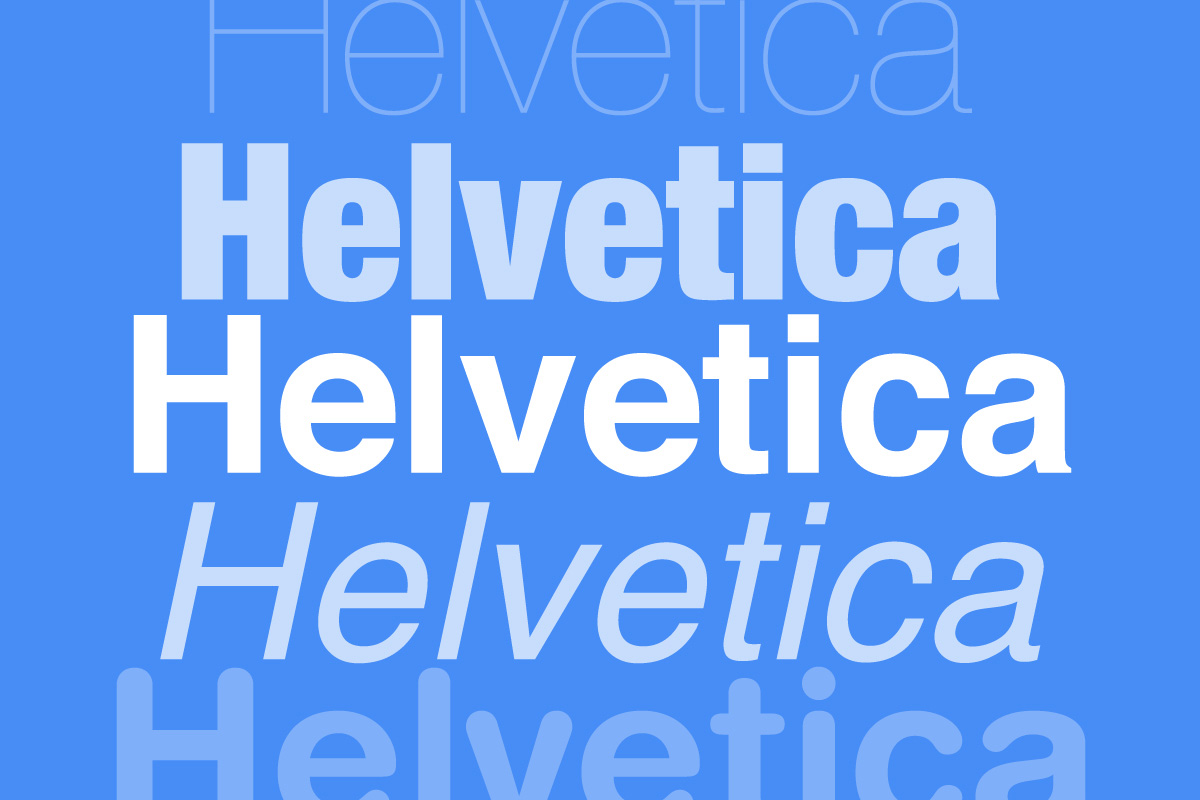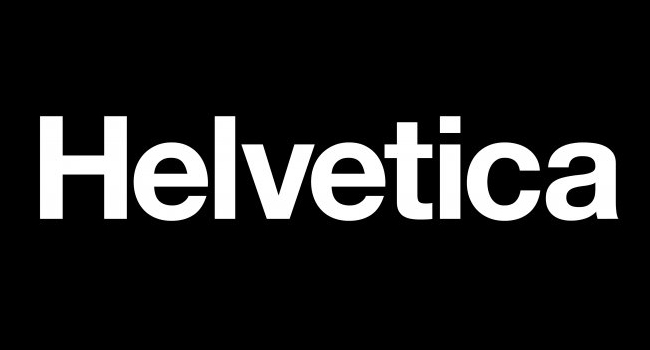
Download font Helvetica – font chữ huyền thoại được mệnh danh là “font chữ hoàn hảo nhất thế giới”, được sử dụng bởi hàng nghìn thương hiệu lớn như BMW, American Airlines, Lufthansa, Toyota. Font Helvetica với phong cách sans-serif trung tính, cân đối tuyệt đối là lựa chọn hàng đầu cho thiết kế bao bì sản phẩm cao cấp, túi giấy thương hiệu và in ấn chuyên nghiệp.
Font Helvetica là gì?
Font Helvetica được thiết kế năm 1957 bởi Max Miedinger tại Haas Type Foundry ở Thụy Sĩ. Tên gốc của font là Neue Haas Grotesk, sau đó được đổi thành Helvetica (từ “Helvetia” – tên Latin của Thụy Sĩ) vào năm 1960 khi Linotype mua bản quyền và phát hành quốc tế.
Helvetica nhanh chóng trở thành biểu tượng của thiết kế hiện đại thế kỷ 20 nhờ phong cách trung tính tuyệt đối, cân đối hoàn hảo. Font này không mang bất kỳ tính cách riêng biệt nào – không cổ điển, không hiện đại quá, không nam tính, không nữ tính – chính điều này khiến nó phù hợp với mọi thương hiệu và mọi thông điệp.
Các phiên bản Helvetica qua thời gian:
• Helvetica gốc (1957): Có các phiên bản Regular, Bold, Light với hệ thống đánh số 55, 65, 75…
• Helvetica Neue (1983): Phiên bản cải tiến với 51 phiên bản khác nhau, từ Ultra Light đến Black, bao gồm cả Condensed và Extended.
• Neue Helvetica (Linotype): Phiên bản chuẩn hóa lại hệ thống đánh số, dễ sử dụng hơn.
• Helvetica World: Mở rộng hỗ trợ nhiều ngôn ngữ hơn bao gồm tiếng Việt, Ả Rập, Hy Lạp…
• Neue Helvetica Paneuropean: Phiên bản mở rộng cho các ngôn ngữ châu Âu.
• Neue Helvetica Pro: Phiên bản chuyên nghiệp với nhiều tính năng OpenType.
• Helvetica Now (2019): Phiên bản hiện đại nhất được Monotype phát hành, tối ưu cho cả in ấn và màn hình.
Helvetica Regular (55)
400 Mô tả sản phẩm, thông tin bao bì (8-12pt).
Helvetica Bold (75)
700 Logo, tên sản phẩm, tiêu đề túi giấy (14-24pt).
Helvetica Black (95)
900 Poster khổ lớn, standee, billboard.
Helvetica Neue Light (35-45)
300 Catalogue cao cấp, brochure thương hiệu luxury.
Helvetica Neue Ultra Light (25)
200 Tiêu đề nhẹ nhàng, thanh lịch trên catalogue.
Neue Helvetica Pro 97 Condensed Black
900 Condensed Tiêu đề mạnh mẽ, tiết kiệm không gian.
Neue Helvetica Paneuropean 93 Extended Black
900 Extended Poster, backdrop sự kiện cao cấp.
• Arial: Font có sẵn trong Windows và Mac, giống Helvetica đến 95%. Đây là lựa chọn an toàn nhất vì đã được Microsoft mua license và cung cấp miễn phí qua hệ điều hành.
• Liberation Sans: Font open source được phát triển bởi Red Hat, clone gần như hoàn hảo của Helvetica. Hoàn toàn miễn phí cho mọi mục đích.
• Nimbus Sans: Font open source tương tự Helvetica, phát triển bởi URW++. Miễn phí và hợp pháp.
• Inter (Google Fonts): Font hiện đại hơn Helvetica, được thiết kế đặc biệt cho màn hình nhưng in ấn rất tốt. Hoàn toàn miễn phí.
• Work Sans (Google Fonts): Font geometric tương tự Helvetica với nhiều weight từ Thin đến Black.
• IBM Plex Sans: Font open source của IBM, phong cách gần Helvetica, chuyên nghiệp.
So sánh với Helvetica:
Font
Độ giống Helvetica License
Phù hợp in ấn
Arial
95% Miễn phí qua Windows/Mac Rất tốt
Liberation Sans
98% Open source Rất tốt
Inter
85% Google Fonts (miễn phí) Xuất sắc
Nimbus Sans
97% Open source Tốt
Ứng dụng font Helvetica trong thiết kế bao bì cao cấp
Font Helvetica mang phong cách trung tính, vượt thời gian, được ưa chuộng đặc biệt trong thiết kế cao cấp:
• Trung tính tuyệt đối, vượt thời gian: Helvetica không mang tính cách riêng, không lỗi mốt. Sản phẩm thiết kế bằng Helvetica từ 50 năm trước vẫn trông hiện đại ngày nay.
• Cân đối hoàn hảo, dễ đọc: Mỗi ký tự Helvetica được thiết kế với sự cân đối tuyệt đối, khoảng cách chữ hoàn hảo, giúp thông tin trên bao bì luôn dễ đọc.
Helvetica Neue (1983) là phiên bản cải tiến với nhiều weight hơn (51 phiên bản), khoảng cách ký tự tốt hơn, và hệ thống đánh số rõ ràng hơn. Helvetica gốc (1957) chỉ có vài weight cơ bản.